BITS 2015 : Bangkok International Typography Symposium
매년 태국 방콕에서 열리는 BITS는 동아시아에서 열리는 유일한 국제 타이포그라피 컨퍼런스이다. 타이포그라피와 타입 디자인을 두루 아우르는 이 컨퍼런스는 TAB(Typographic Association of Bangkok)와 Cadson Demak가 주최하며, Goethe Institute, British Counsil, Korean Cultural Center 그리고 Font Bureau가 후원한다.
BITS 2015 : Bangkok International Typography Symposium
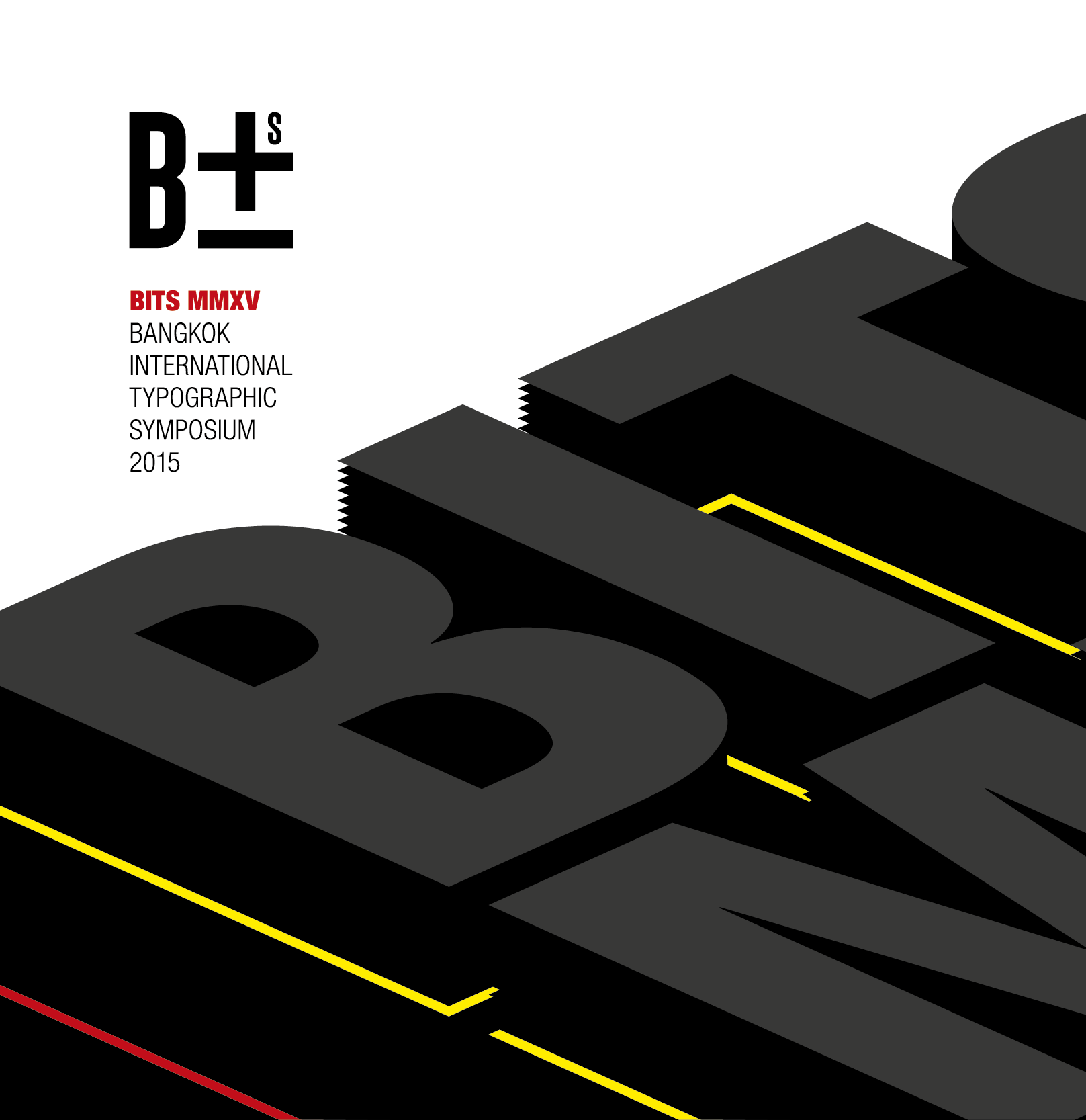
이번 행사는 컨퍼런스뿐만 아니라 워크샵이 포함되어 있었으며, 워크샵은 10월 30일 TCDC (Thailand Creative & Design Center)에서, 컨퍼런스는 10월 31일부터 11월 1일까지 이틀 동안 BACC (Bangkok Art & Cultural Center)에서 진행되었다. 산돌커뮤니케이션에서는 석금호 대표를 비롯한 디자이너들이 참여하였으며, 그 현장의 분위기를 김초롱 PD와 이슬기 매니저가 글과 사진으로 전한다.
Workshop Day (10/30)
본격적인 컨퍼런스에 앞서 다양한 워크샵들이 열렸다. 가장 먼저 산돌의 석금호 대표가 ‘Making Korean Name used with Thai Letter'(태국 문자를 이용하여 한글 이름 만들기)라는 제목으로 진행하였다. 태국 문자를 가지고 자신의 이름을 한글로 만들어보는 시간이었다.
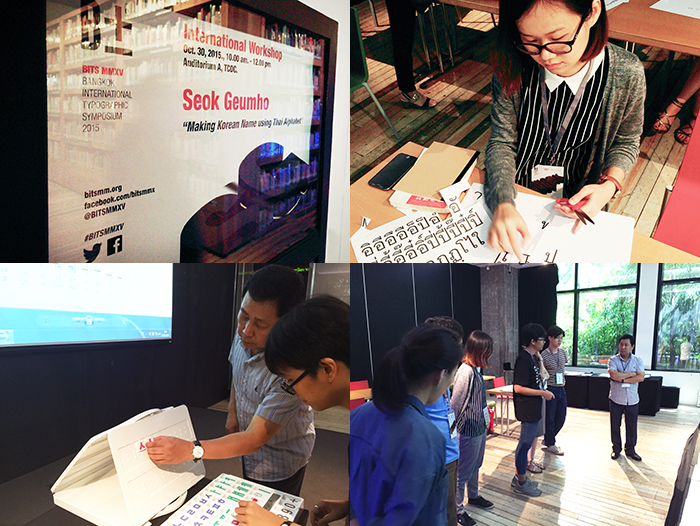
참여자들은 한글로 표기된 자기 이름의 시각적 형태를 살펴본 후 태국 문자에서 어떤 부분을 활용할 수 있을지를 고려하여 구상하고, 그 구상이 끝나면 준비된 프린트물 재료를 활용하여 한글을 완성하는 내용이었다.
Conference Day.1 (10/31)
Font Bureau의 디자이너인 David Jonathan Ross는 ‘Draw a Little, Code a Lot’이라는 주제로 슈퍼패밀리 폰트 제작에 도움이 되는 여러 프로그램을 통해 우리가 어떻게 손쉽게 폰트를 변형할 수 있는지에 대해 이야기했다. 또한, 이를 통해 우리가 얻는 이점과 주의해야 하는 점들에 대해 논의했다.
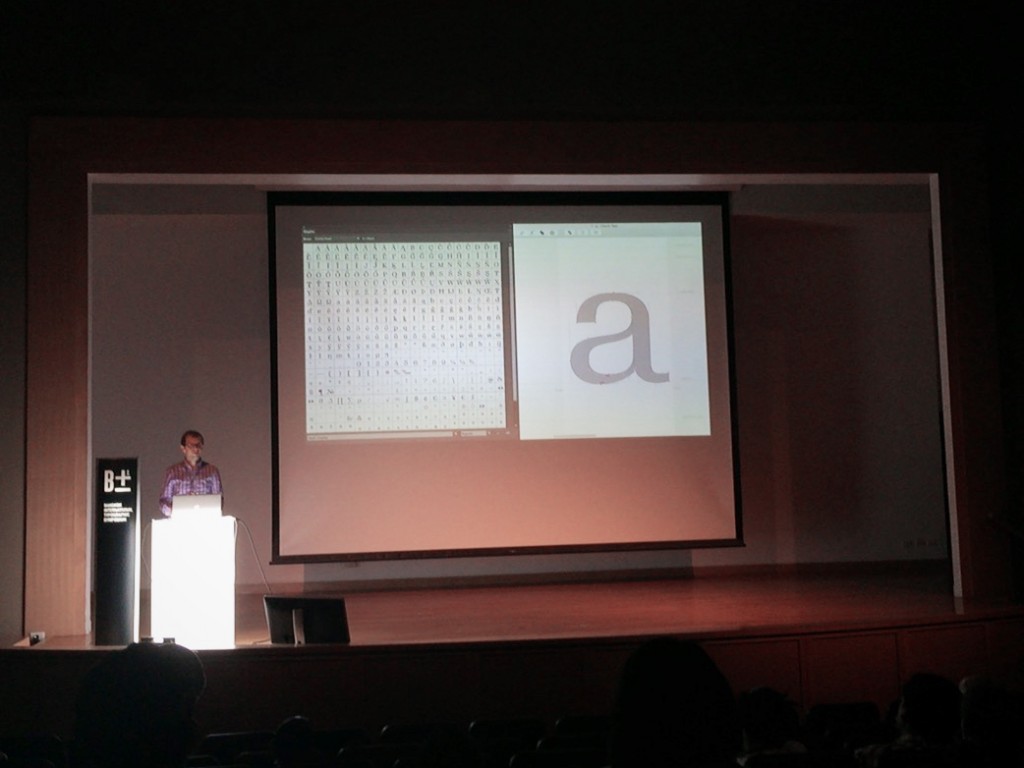
더불어 ‘코드’를 위해서 자신이 개발한 ‘INPUT’이라는 프로젝트를 소개했다. 이는 스크린을 위한 고정폭 픽셀 폰트의 미적 조형감을 따르고 있지만 보다 더 다듬어진 정교한 형태를 갖추고 있었다. 무엇보다 굵기와 너비의 다양성을 갖추고 있어, 프로그래머들이 작업할 때 쉽게 정보를 구분할 수 있도록 하였다.
산돌의 석금호 대표는 ‘Structure and Features in Hangul and fonts development'(한글의 구조와 특징들, 그리고 폰트 개발사례)라는 제목으로 발표하였는데, 한글만이 지니고 있는 독특하고 체계적인 자형 구조에 대해 설명하였다.
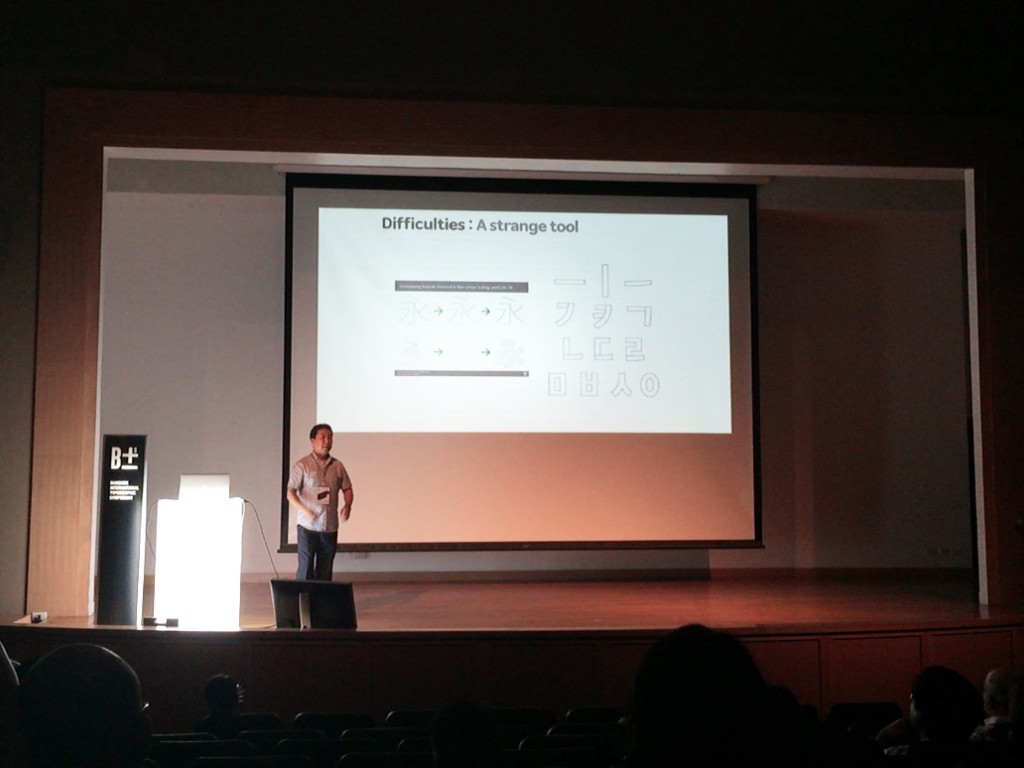
한글은 구조적으로 단순하게 보이나 각 문자의 시각적인 균형을 해결하는 데는 세계 문자 중에서 가장 까다로운 특성이 있다는 것을 설명하고, 이러한 특성들이 실제 상업용 폰트로 개발되는 과정에서는 어떻게 다루어지는지 보여주었다.
Conference Day.2 (11/1)
Verena Geriach는 ‘Search, find, and make: The city as open source for type design’ 라는 주제로 강연하였다. 그녀가 타입 작업을 하는데 있어 가장 큰 영감을 받은 것은 20세기에 존재했던 간판 같은 사인물들이었다. 그녀는 그 시대의 Shop signage를 모티브로 하여 그 형태를 딴 모던하고 유니크한 그녀만의 폰트를 디자인했다. FF Karbid가 그것들 중 하나로 1900년대 간판 레터링을 리디자인한 것이다. 그녀는 오래된 간판 레터링에 있는 각각의 모양과 구성요소들을 따서 디지털 폰트로 리메이크하였으며 이는 단순 컴퓨터 작업으로만 이루어졌다.
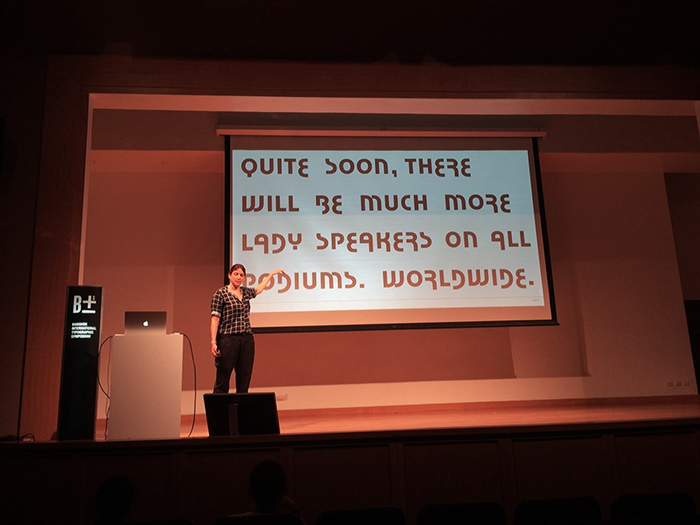
우리는 그녀가 쓴 책을 직접 선물받기도 했는데, 책에는 그녀가 역사적인 타이포그라피에 대해 어떻게 생각하는지, 그녀가 어떻게 폰트를 리메이크하여 만들어내는지에 대해 알 수 있었다.
그녀가 강연 중에 했던 말이 기억에 나는데, “이것들은 정말 내가 좋아하고 재밌어하는 일들이고, 내가 폰트 디자인에 영감을 받는 데 있어 가장 중요한 것은 다행히도 내가 베를린에 있었다는 것이다.” 그녀는 이러한 작업들을 하며 정말 즐기는 것같이 보였고 작품에서도 그녀의 아이덴티티가 분명히 드러나 있어 인상적이었다.
Supakit Chalermlarp는 실제로 폰트 개발 후반작업(post production)을 하며 자주 접했던 문제점 중 태국의 성조 부호와 모음의 위치에 관한 발표를 하였다.
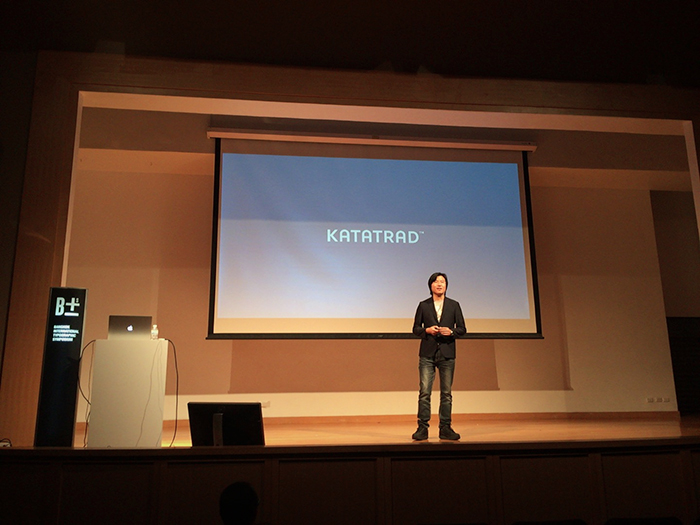
손글씨와 다르게 각각의 글자가 폰트화되면서 발생하는 여러 문제점들을 설명하고, 태국어 폰트에 있어 올바른 성조 부호의 위치에 대한 이야기를 나누었다. 이를 통해 태국 폰트 디자이너들이 작업을 하는 데 있어 실제적 도움을 주고자 하였다.
Mark De Winne은 ‘Singapore on Display’라는 주제로 싱가포르의 ‘Typographical heritage’에 대해 이야기했다. 싱가포르는 현재 과도기를 거치고 있으며 새로운 것을 짓기 위해 오래된 것을 부수면서 문화적 유산들이 점점 사라져 가고 있다고 말했다. 이런 문화적이고 역사적인 부분들과 더불어 싱가포르의 옛 타이포그라피에 대해 공유했다.
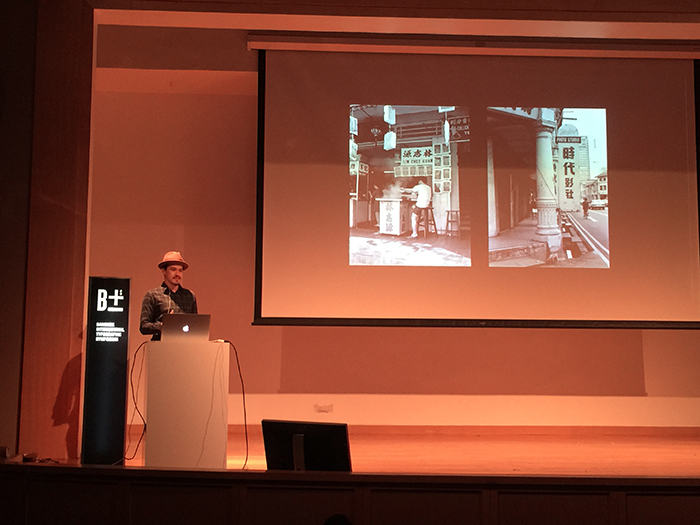
그가 준비한 화면에서는 오래된 건물에 남은 문구들(대부분이 손으로 쓴)이 보여졌고, 전혀 비슷하지 않은 서체들의 조합이-붓으로 쓴 듯한 중국어와 산세리프 라틴폰트가 만나-희한하지만 그 속에서도 일관성 있는 모습을 보여주었다. 언뜻 보기엔 희한하고 어지럽지만, 옛 싱가포르의 역사가 그대로 묻어있다는 걸 느낄 수 있었다. 또한, 2015년은 싱가포르 개국 50주년이 되는 해로, 그는 디자이너로서 이를 기념하기 위해 싱가폴을 상징할 수 있는 폰트를 만들고자 한다고 밝혔다.
영국의 그래픽 아티스트이자 디자이너인 Anthony Burrill은 친근함 속에서 어떻게 영감을 받고 그것을 표현하는지, 세상의 디자인에서 새로운 아이디어를 어떻게 찾아내는지 설명했다.
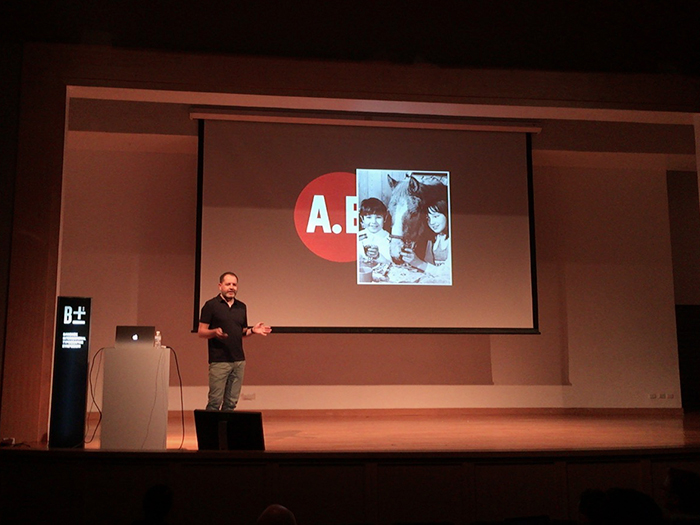
그의 강연에서 가장 기억에 남았던 것은 “그래픽 디자이너로서 사회를 위해 할 수 있는 일은 이렇게 포스터로 목소리를 내는 일밖에 없다“라는 말이었다. “왜 꼭 포스터로만 (종이에 실크스크린으로) 디자인을 하느냐, 티셔츠나 다른 매체는 생각해본 적이 없는가?”라는 질문에 “나는 다른 매체로 표현하는 것에 대해 평소에 많이 고려하지 않는다. 그것들의 기능은 매우 다르다. 하지만 포스터가 내는 만큼의 목소리는 가질 수 없다” 라고 대답했다.
Christian Schwartz은 ‘Credibility, Legibility, and Style’이라는 주제로 강연했다. 그는 손으로 직접 활자를 조판하는 시대부터 시작해서 기계식 조판과 사진식자를 거쳐 디지털 조판에 이르기까지, 활자를 제작하는 매체의 변화로 인해 활자가 가지게 되는 여러 특성들에 관해 설명했다. 하지만 가독성은 신뢰성의 신호와도 같다는 말과 함께, 가독성을 위해 변하지 않은 특징으로 큰 x-height와 약한 대비 그리고 단순한 디테일을 꼽았다.
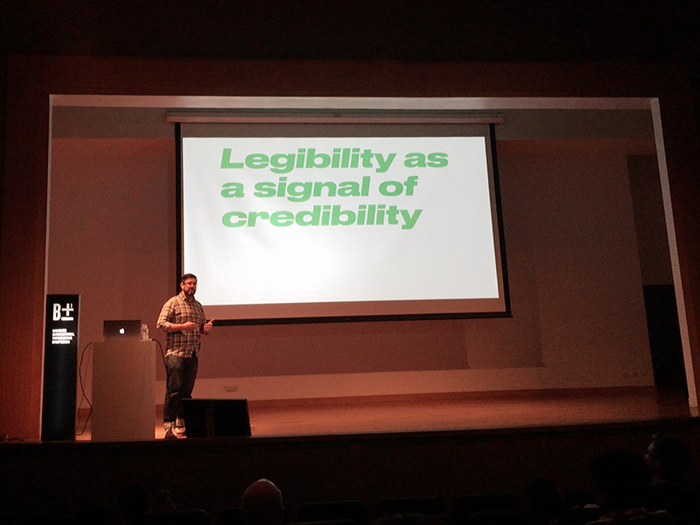
또한, 인쇄와 스크린에 똑같은 서체를 사용한다 해도 일관성을 보장하는 데에 충분하지 않다는 점에 대해 이야기했다. 오히려 타이포그래피의 다른 요소들이 중요한 역할을 하는 경우가 많으며, 텍스트에 사용된 서체가 같다고 해도 칼럼의 너비, 서체의 크기, 행간 등이 극단적으로 바뀌면 일관성을 확보하기 어렵다고 예를 들었다.
이런 주장을 잘 뒷받침하는 것이 바로 그가 최근에 작업한 McClatchy(2015) 폰트 패밀리이다. 이는 미국 전역에 걸쳐 29개의 일간지를 발행하는 McClatchy라는 클라이언트와 함께한 작업이었다. 그들은 시각적 일관성을 유지하면서도 완벽하게 같은 구조가 아닌 개별성을 가진 패밀리를 원했다. 결과적으로 개별 형태와 구조는 다르지만 같은 굵기와 글자폭, x-height를 가지고 있어 어떤 조판에서 글자를 바꾸더라도 타이포그래피나 레이아웃이 그대로 유지되는 폰트를 개발하였고, 시각적 일관성을 단순히 글자의 모양을 넘어서 타이포그래피의 다른 요소를 유지하는 방법으로 해결하였다.
BITS : Bangkok International Typography Symposium
-일시: 2015년 10월 30일 – 11월 1일
-장소: 태국 방콕, TCDC (Thailand Creative & Design Center) & BACC (Bangkok Art & Cultural Center)
-주요 강연자: Anthony Burrill, Christian Schwartz, Dave Crossland, David Jonathan Ross, Mark De Winne, Panuwat Usakulwattana, Parinya Rojarayanond, Pracha Suveeranont, Seok Geumho, Smich Smanloh, Suppakit Chalermlarp, Verena Gerlach